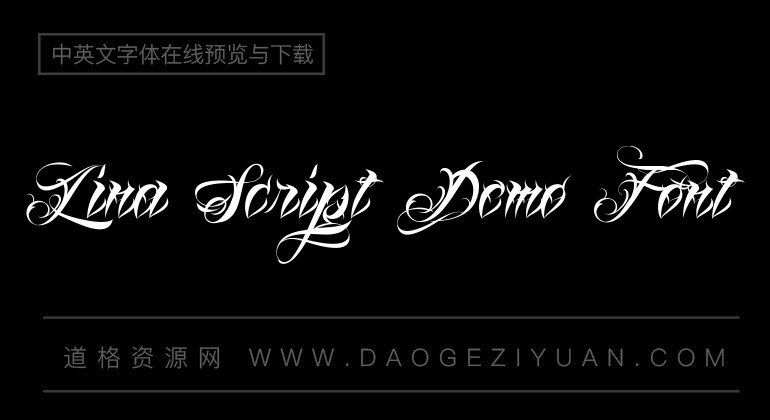
Lina Script Demo Font 是一种优美的手写草书体字体。该字体的特点是字母之间的连贯性,使得文本看起来更加自然流畅。 它的笔画粗细变化适度,有一种不规则的感觉,其中有些字母会形成优美的卷曲。 它适用于设计卡片、海报和标语等需要一些手写风格的场合,更加趋向于优美、可读和精细。内容介绍
Lina Script Demo Font是一款非常不错的手写艺术字体,具有很好的视觉感,适合于文化类的宣传设计、商业类品牌的广告和产品包装设计以及个性化文字排版等较多场景。